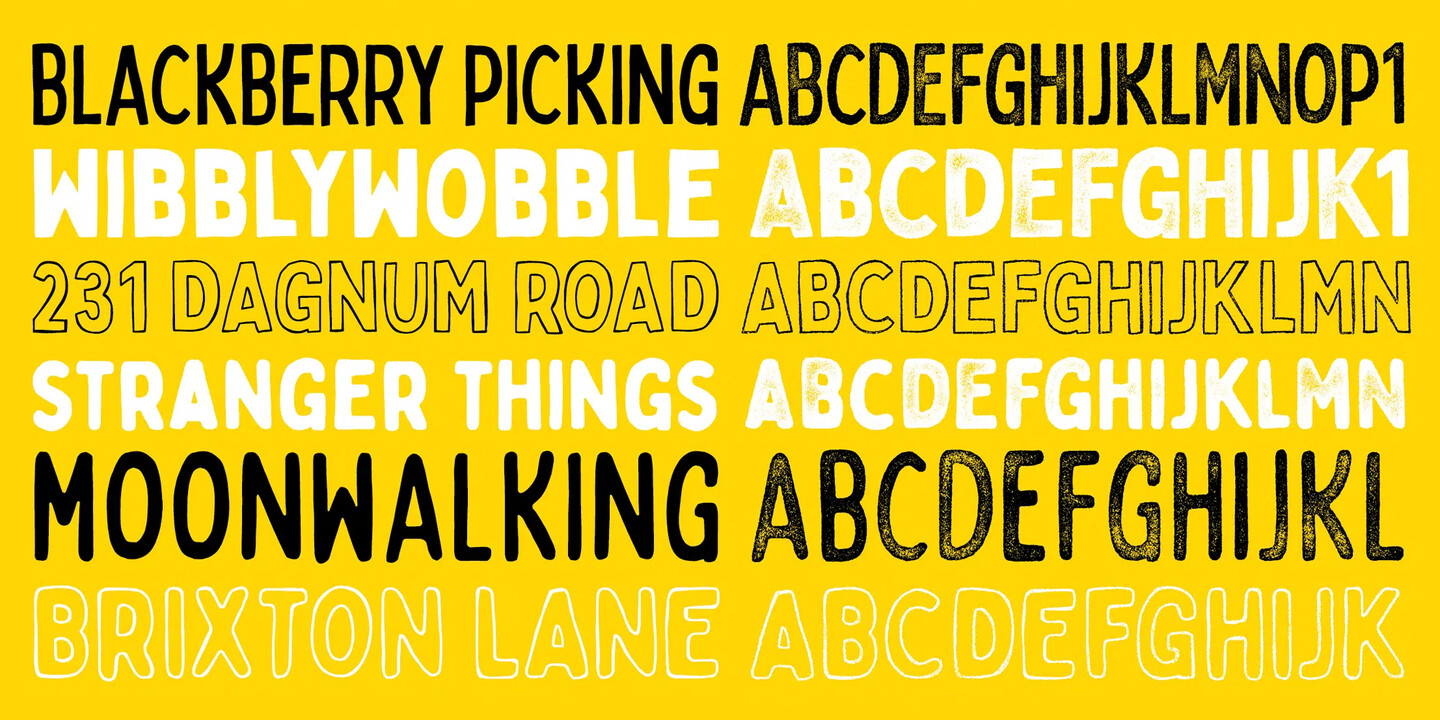
Font von Tom Chalky
Tom Chalky ist ein im Vereinigten Königreich ansässiger Schrift Foundry die sich auf handgefertigte, rustikale und ausdrucksstarke Schriften spezialisiert hat. Seit 2012 ist die Foundry ein Portfolio einzigartiger und kreativer Font entwickelt, denen talentierte Designer und Marken weltweit vertrauen.
In der Bobby Jones Font finden Sie 16 schrullige, handgefertigte Fonts, die vor Persönlichkeit nur so strotzen und bereit sind, in einer Vielzahl kreativer und lustiger Designprojekte die Hauptrolle zu spielen. Wenn Sie mit einer Werbekampagne, einem Logodesign, Bekleidung, gedrucktem Briefpapier und all den anderen guten Dingen die Blicke auf sich ziehen wollen, dann keine Sorge. Bobby hat alles für Sie. Wir alle haben Unvollkommenheiten und Bobby ist da keine Ausnahme! Seine Umrisse sind etwas unregelmäßig, seine Ecken sind unregelmäßig, seine Geraden sind nicht gerade, aber das macht ihm nichts aus. Eigentlich ist er zu sehr damit beschäftigt, mit seinen Sachen zu protzen.
Die TC Antiquated Kollektion im Vintage-Stil Font ist da! Dieses vielseitige Trio von Schriften, das jeweils in drei verschiedenen Gewichtsklassen erhältlich ist, wurde als wunderbare Mischung aus modernem und rustikalem Stil entworfen.
Diese Kollektion ist ideal für moderne Branding-Projekte mit einem Hauch von Vintage, rustikale Hochzeitseinladungen und Briefpapier, Designprojekte mit historischen Themen und redaktionelle Arbeiten! Ich verwende diese Fonts besonders gerne in kleineren Formaten mit großen Abständen, wie sie in den Präsentationsbildern zu sehen sind.
Bringen Sie einen Spritzer Spontaneität und Flair in Ihre Entwürfe mit "Swangler", einer Schrift , die ebenso frech und selbstbewusst wie ausdrucksstark ist. Swangler ist nicht nur zum Lesen, sondern auch zum Erleben gedacht und damit perfekt für Projekte, die einen Hauch von Persönlichkeit und Wirkung erfordern.
Swangler zeichnet sich durch seinen handgefertigten Look aus, der von dynamischen Veranstaltungsplakaten und lebendigen Marketingkampagnen inspiriert ist. Jede Figur ist in vier verschiedenen Stilen erhältlich, so dass Designer die Möglichkeit hat, sie für einen wirklich individuellen Ausdruck zu mischen und anzupassen. Dank dieser Vielseitigkeit eignet sich Swangler ideal für Branding, Werbung und redaktionelles Design, wo ein Statement gefragt ist.
Tom Chalky
Besessen von Handgeschriebenem, Handgemaltem und Unvollkommenem. Fast jedes Design kann von der Handschrift eines Menschen profitieren oder zumindest den Anschein einer solchen haben. Es ist greifbar, fühlbar und authentisch. Es hebt sich von unserer sauberen und knackigen digitalen Welt ab, und es ist dieser charismatische und ausdrucksstarke Designstil, den ich in jedem meiner Fonts anstrebe.
Regisseur und Schriftgestalter
Tom Chalky
Meine Designreise begann als Teenager, der als "Photoshop Kid" bekannt war und mit Dreamweaver Webseiten für örtliche Fahrradläden und Werkstätten erstellte (das waren noch Zeiten!). Während meines Studiums gründete ich zusammen mit meiner jetzigen Frau Abbie einen Design-Blog, Inspiration Hut. Der wahre Heureka-Moment kam, als ich die Typografie entdeckte, was Jahre der kreativen Erforschung und Selbstfindung in der herrlichen Welt des Schriftdesigns auslöste. Nichts von alledem war geplant - ich lasse mich einfach treiben und nutze jede Gelegenheit. Wenn ich nicht gerade Buchstaben zeichne, bin ich beim Bouldern anzutreffen, wobei ich oft feststelle, dass ich mich eigentlich mehr strecken sollte.